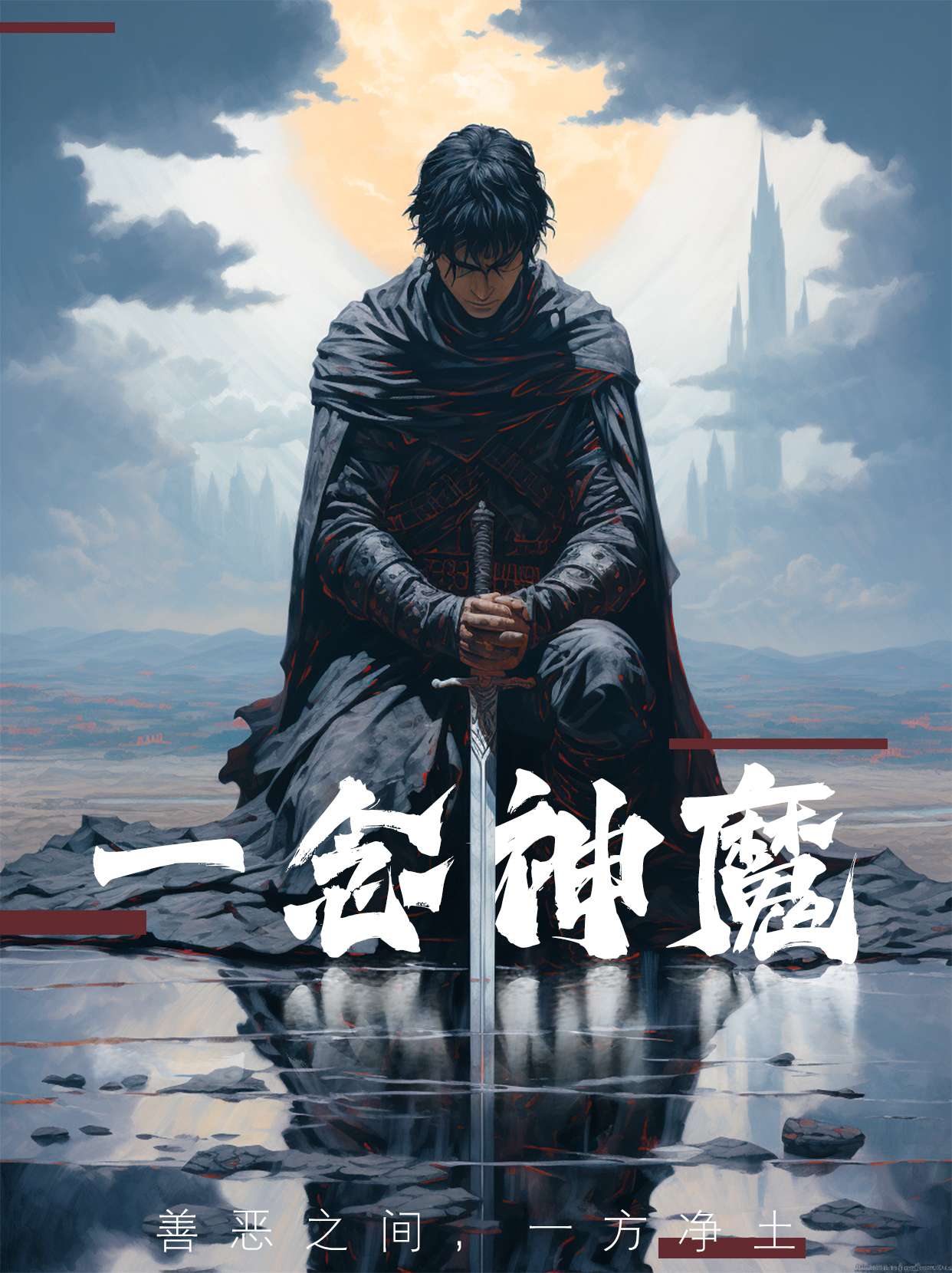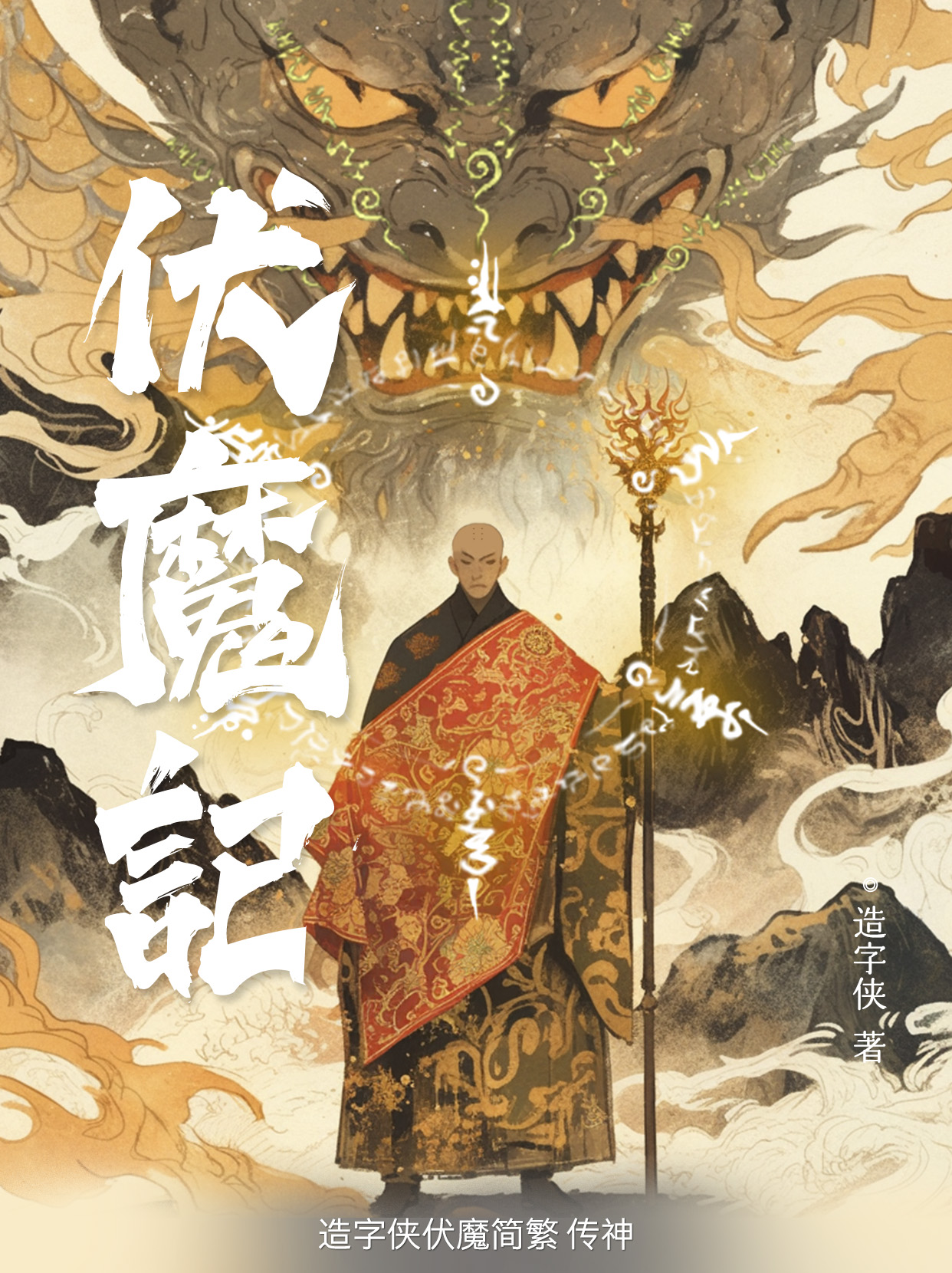
造字侠伏魔简繁 传神
PlayFont-HeroGBT
字体名称:
造字侠伏魔简繁 传神
字符集:
GBT
字体语言:
简繁
书体类型:
毛笔字体
字体类型:
普通字体
字体字重:
大黑(Bold)
斩妖伏魔耀苍穹
笔墨浓厚,粗细对比较为明显,字体结构较为中正,字体里笔画的“勾、提、挑、捺”等笔画特点明显、夸张,极具视觉冲击力,单字结构收放自如。